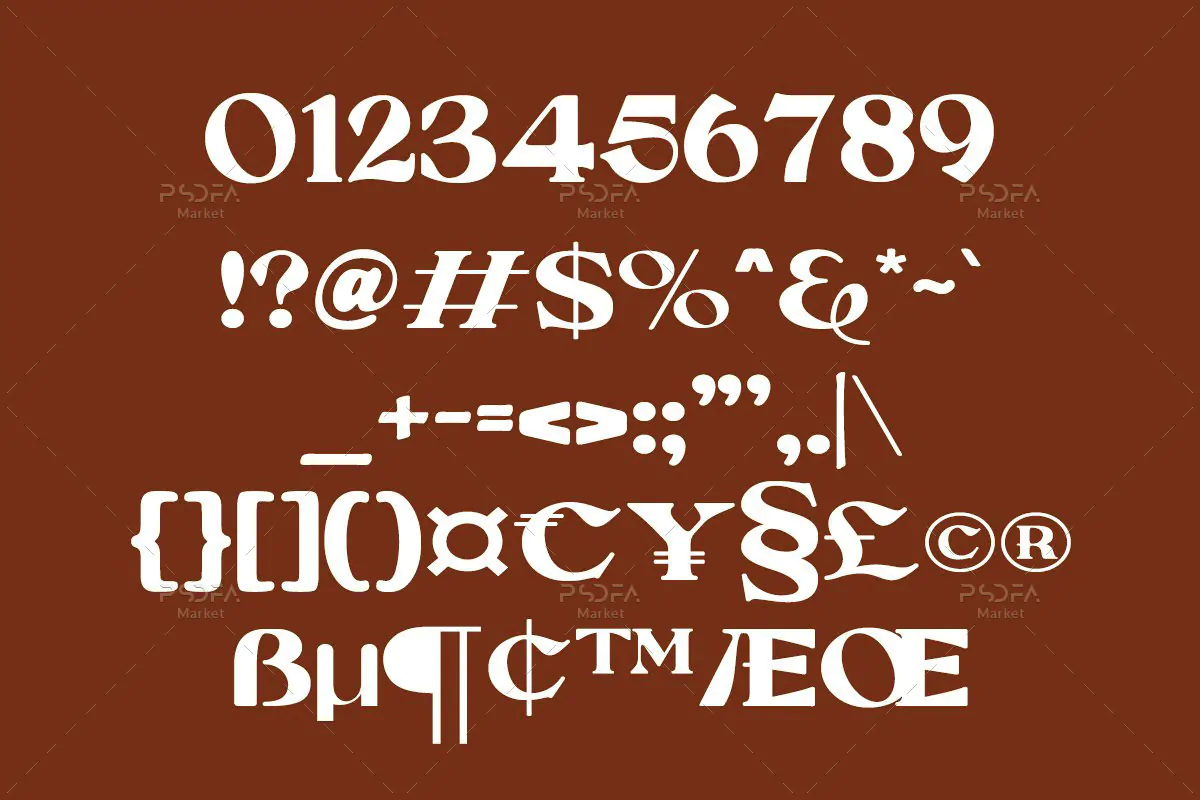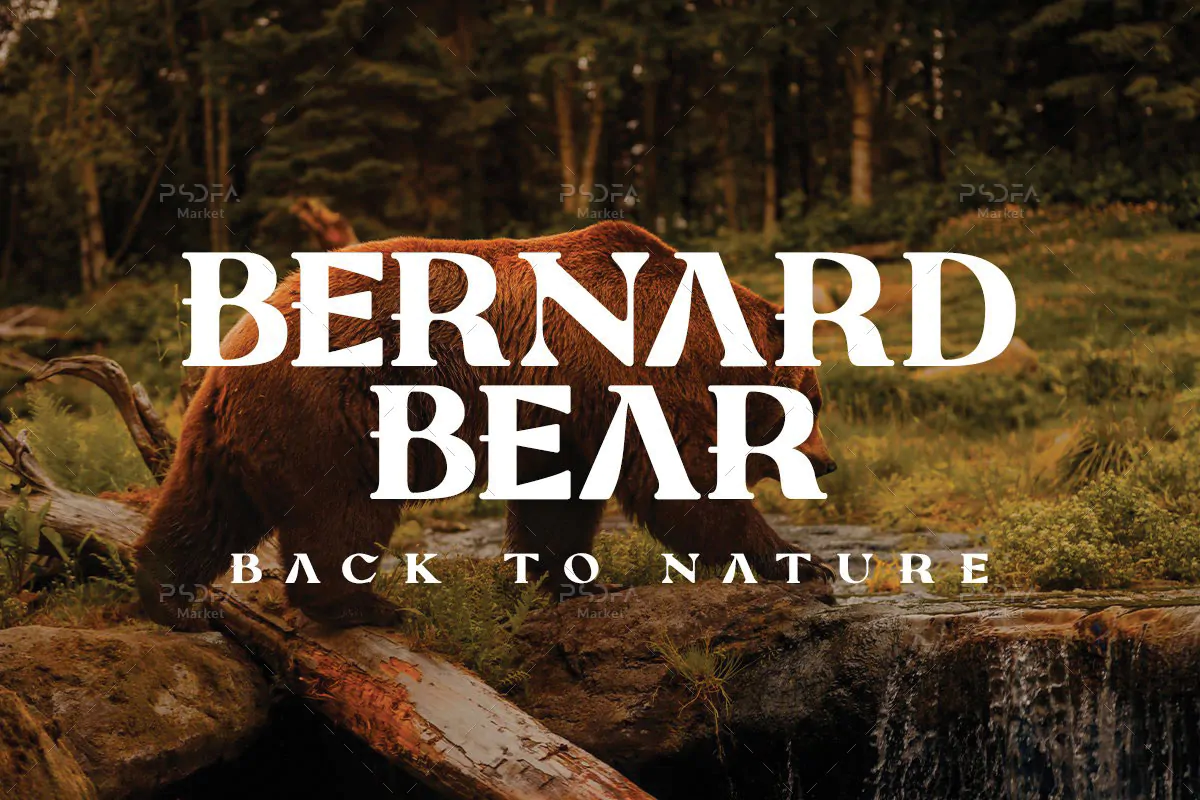
سریف فونت کلاسیک و رترو Neo Qiltas
سریف فونت کلاسیک و رترو
سریف فونت کلاسیک و رترو Neo Qiltas یک قلم زیبای انگلیسی است که مناسب جهت استفاده در طرح و پروژههای گرافیکی مختلف میباشد. این فونت زیبا با وزن معمولی (Regular) طراحی شده است که میتوانید از آن در طراحی پوستر، کارت ویزیت، بسته بندی محصولات، تراکت، بروشور، کتب و مجلات و … استفاده کنید.